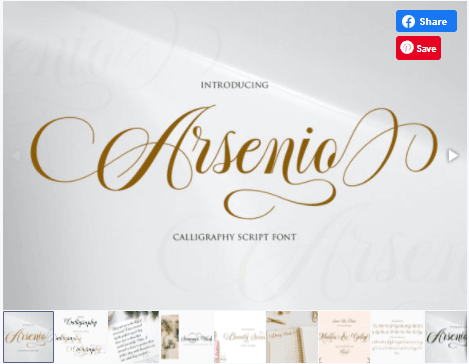
Arsenio Script Font
Arsenio Script выглядит одинаково очаровательно и элегантно. Он выглядит потрясающе на свадебных приглашениях, благодарственных открытках, цитатах, поздравительных открытках, логотипах, визитных карточках и любом другом дизайне, который требует рукописного прикосновения. Этот шрифт имеет кодировку PUA, что означает, что вы можете легко получить доступ ко всем глифам и росчеркам!